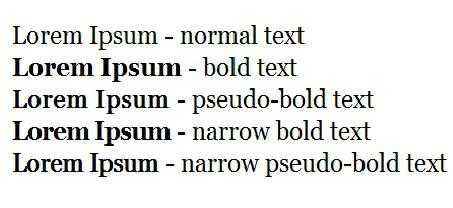
Как шрифт сделать жирным в css – Свойство font-weight — жирный текст
Как сделать в CSS жирный шрифт?
Чтобы сделать в CSS жирный шрифт, следует использовать ряд стандартных команд. Но можно воспользоваться и нестандартными вариантами, которые дают интересный эффект. Жирное начертание применяется для выделения строго определенного фрагмента текста. CSS нам помогает присвоить такой шрифт любому словосочетанию или даже отдельной букве. Если вы до сих пор используете HTML-теги для достижения этого эффекта, вам нужно пересмотреть свои взгляды на программирование, так как каскадные таблицы стилей дают вам как разработчику больше возможностей. О некоторых из них мы поговорим в этой статье.
Присваивание
Жирный шрифт CSS присваиваете с помощью простого правила: font-weight. В качестве значения можно указать различные комбинации. Например, можно написать свойство «font-weight: bold», что означает полужирное начертание. В качестве стандартного значения используется запись «normal». Помимо ключевых слов можно использовать обычные цифры. Условные единицы колеблются от 100 до 900, где 400 соответствует команде «normal». А это означает, что если установить значение меньше 400, то шрифт будет терять свою насыщенность, а если более, то приобретет жирный вид. Это позволяет производить ручную настройку начертания.
В CSS жирный шрифт может присваиваться, исходя из родительского элемента. В каскадных таблицах существует две команды («bolder» и «lighter»), которые могут увеличивать или уменьшать насыщенность начертания. Значения будут изменяться в зависимости от родительского элемента. Свойство «font-weight» может записываться в краткой форме – «font», куда можно записать все характеристики шрифта.
Цель
Присваивать такой CSS-шрифт можно любому элементу HTML или XHTML. Эффект будет виден только в том случае, если тег содержит в себе текст. В HTML существует аналог свойству «font-weight». Если поместить текст между тегами <strong>, то он станет более насыщенным. Его свойство полностью идентично значению «bold». Некоторые разработчики не видят разницы между тегом <strong> и CSS жирный шрифт. А различия есть. Тег имеет свою собственную смысловую нагрузку, используется для действительно важной информации. А CSS-свойство – это всего лишь декоративное значение, употребляемое для украшения текста. Пускай данная разница и не ощущается при чтении, но, как советует консорциум всемирной паутины, все должно стоять на своих местах. Такой порядок в коде увеличит жизнь вашим страницам. Ведь не за горами то время, когда браузеры научатся использовать другой способ визуализации текста, где будет выделяться смысловое и декоративное значение. Не стоит об этом забывать при создании своих страниц.
Существующий в CSS жирный шрифт позволяет уменьшить исходный код страницы. Ведь нет необходимости использоваться тег <strong>. Достаточно просто заключить необходимый текст в определенный класс. А если нужно отменить жирное начертание, то нужно всего лишь исправить один файл с каскадными таблицами. Но не забывайте, что нельзя злоупотреблять данным свойством, так как излишнее использование различных декоративных приемов может испортить текст. Желательно применять жирный шрифт только тогда, когда это действительно нужно, например, для выделения заголовков или названия определенного раздела.
Учебник CSS для начинающих. Свойства шрифта.
Глава 3
В предыдущей главе мы рассмотрели свойства текста, в этой поговорим о том что можно сделать с шрифтом используя инструменты CSS.
Свойство font-style, в зависимости от выбранного значения, определяет стиль шрифта.
Шрифт может иметь следующие стили:
- normal — обычный (по умолчанию)
- italic — курсив
- oblique — наклонный
Пример:
Чем отличается курсив от наклонного текста? Курсив — это своего рода шрифт взятый из библиотеки шрифтов, а наклонный текст — это результат работы алгоритма, где каждый символ слегка наклоняется в правую сторону.
Весьма интересное свойство шрифта font-variant позволяет делать строчные буквы заглавными и уменьшенными.
Значения:
- normal — нормальный (по умолчанию)
- small-caps — все буквы заглавные и уменьшенные
Свойство CSS font-size — определяет размер шрифта.
Размер шрифта может быть задан в процентах или пикселях и любых других допустимых единицах измерения CSS, а так же абсолютным или относительным значением.
значения абсолютного размера шрифта:
- xx-small — очень очень маленький
- x-small — очень маленький
- small — маленький
- medium — средний
- large — большой
- x-large — очень большой
- xx-large — очень очень большой
значения относительного размера шрифта:
- larger — больше чем размер шрифта родительского элемента
- smaller — меньше чем размер шрифта родительского элемента
Существующий в CSS жирный шрифт позволяет уменьшить исходный код страницы. Ведь нет необходимости использоваться тег <strong>. Достаточно просто заключить необходимый текст в определенный класс. А если нужно отменить жирное начертание, то нужно всего лишь исправить один файл с каскадными таблицами. Но не забывайте, что нельзя злоупотреблять данным свойством, так как излишнее использование различных декоративных приемов может испортить текст. Желательно применять жирный шрифт только тогда, когда это действительно нужно, например, для выделения заголовков или названия определенного раздела.